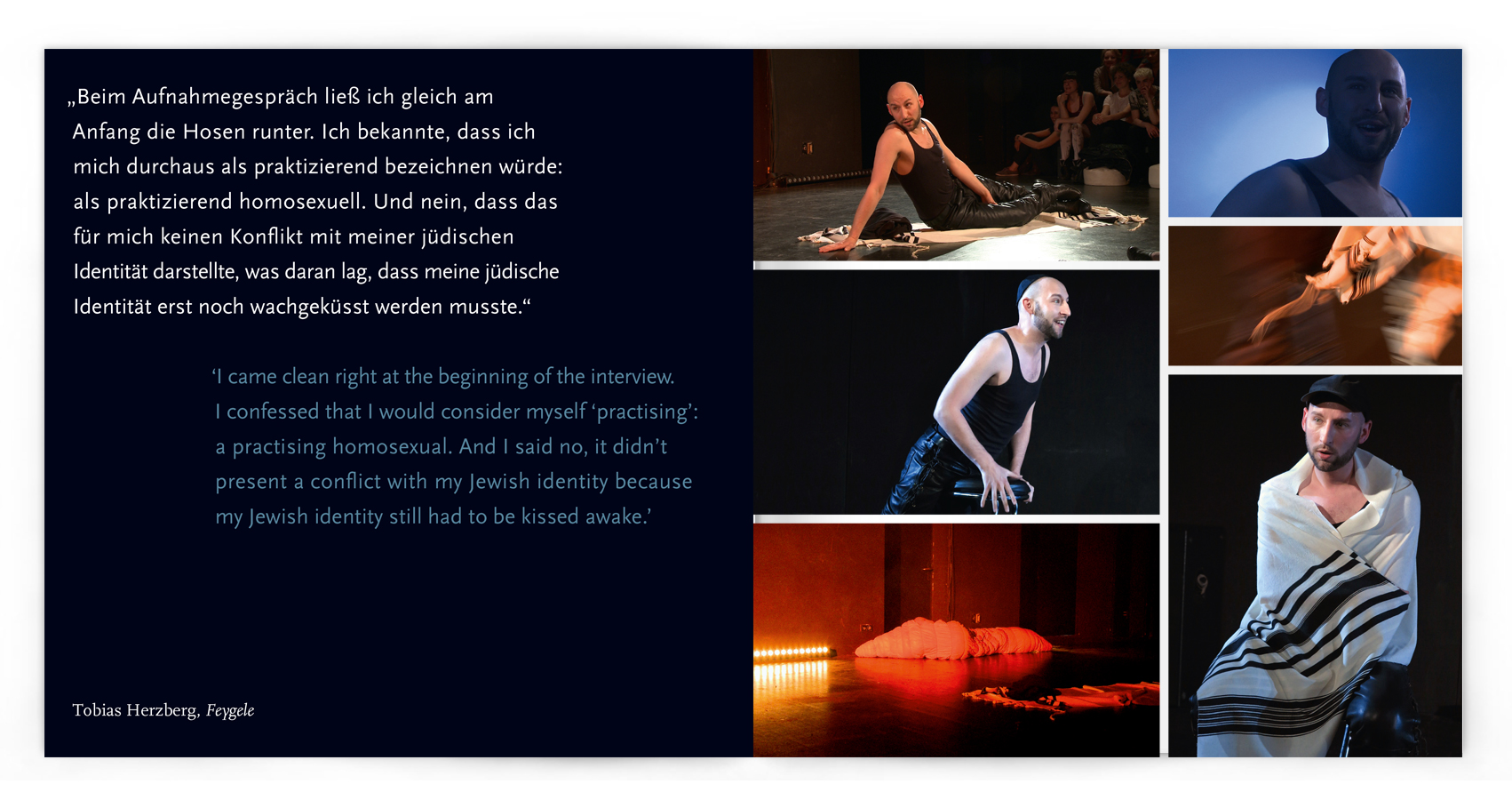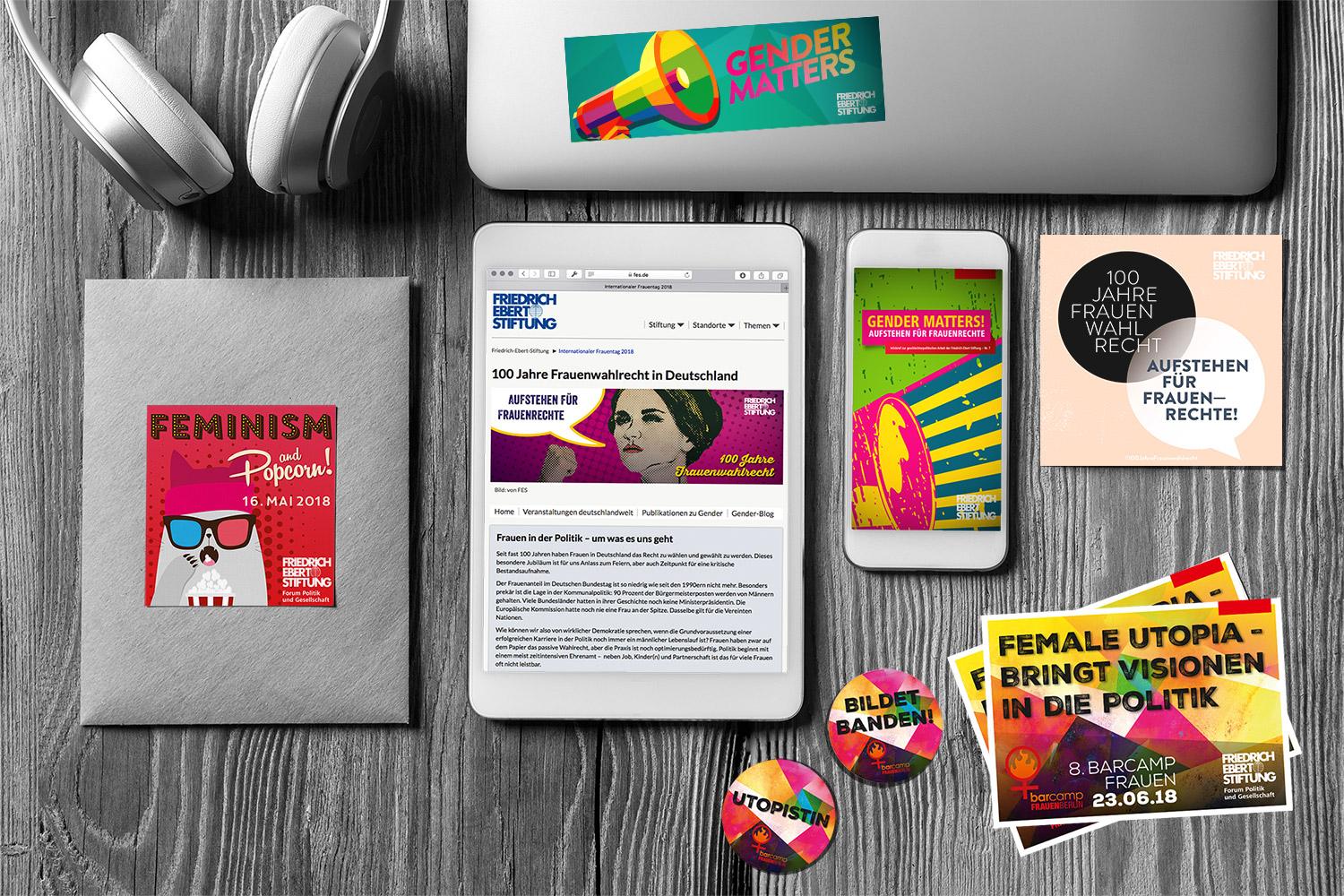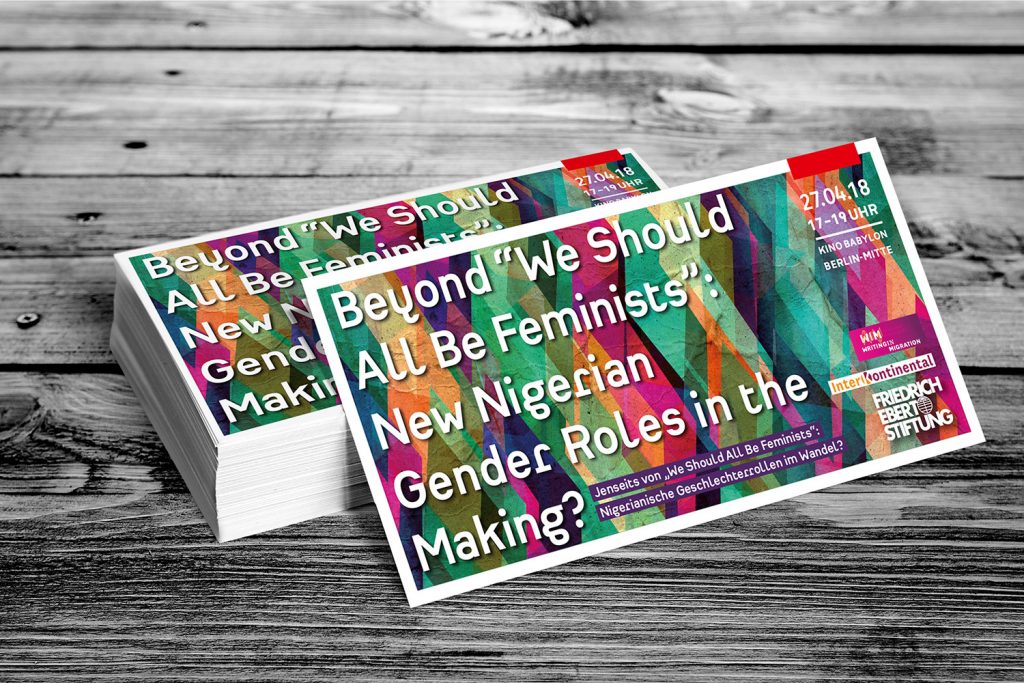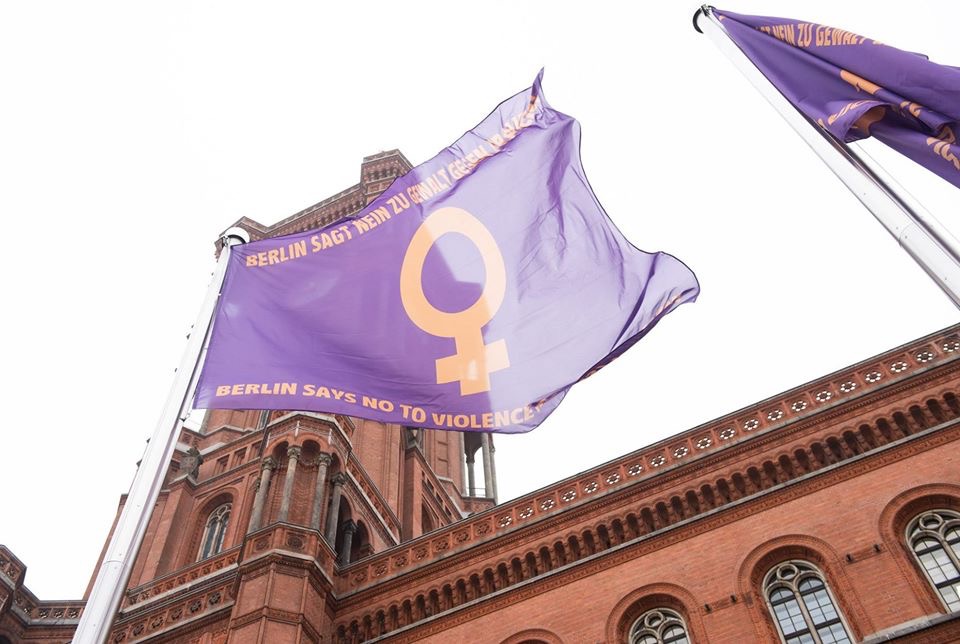
Visuelle Kommunikation // Editorial Design – Chapbooks // August 2020
Im Verlagshaus Berlin haben wir eine neue Reihe für Chapbooks entwickelt: In der edition zwanzig erscheinen Chapbooks, die Lust machen auf das Entdecken neuer poetischer Stimmen. Wir wollen Autor*innen eine erste Plattform zur Publikation und Zusammenarbeit bieten, noch bevor ein umfangreiches Manuskript in üblicher Debutlänge vorliegt.
Für die neue Edition habe ich das gestalterische Konzept entwickelt: handliche Bücher mit Klappumschlag, Fadenknotenbindung und gedruckt auf Fedrigoni´s neuem Arena-Papier leuchten im sommerlich frischen Pantone 811. Kleine typografische Schätze, die dazu einladen, neue Lyrik zu entdecken.
In unserer ersten Edition erschienen »BARBARA« von Barbara Juch und »lustdorf« von Alisha Gamisch starke lyrische Stimmen, die noch viel von sich hören lassen werden.
Visuelle Kommunikation // Gestaltung von Logo & Printmedien // August 2020
Das Projekt »Dagesh. Jüdische Kunst im Kontext« engagiert sich für Bildung und Vermittlung jüdischer Gegenwartskünste. Gestaltung von Logo, Falzflyer für das Bildungsprogramm »DAGESH on Tour« und Visitenkarten. → www.dagesh.de
Visuelle Kommunikation // Essay & Editorial Design // Dietz Verlag // August 2020
Von Franziska Richter, der Herausgeberin der Anthologie »Echoräume des Schocks« wurde ich neben vielen anderen Kreativen und Kulturschaffenden eingeladen, einen Text zur Anthologie über die Zeit des Lockdown beizusteuern. Entstanden ist der Essay »Ich glaube an die Chance, die in Vagheit liegt«, der persönliche Erfahrungen in meinen Rollen als Verlegerin, Typografin und Lehrende in einer Zeit großer Unsicherheiten reflektiert. Den Essay könnt ihr ab Seite 66 direkt im Buch nachlesen.
In 25 Beiträgen zeichnen Kulturschaffende und Kreative den Widerhall dieser Zeit auf, berichten von Ereignissen aus Politik und Gesellschaft und erzählen von Ängsten und Hoffnungen in ihrem Alltag im Ausnahmezustand. Sie vermessen den Schock, der den Kulturbereich getroffen hat und stellen sich die Frage, wie Kunst und Kultur in und nach der Corona-Zeit gefördert beziehungsweise gestärkt werden können.
ECHORÄUME DES SCHOCKS
Wie uns die Corona-Zeit verändert
Reflexionen Kulturschaffender und Kreativer
Franziska Richter (Hg.)
Gestaltet wurde das Buch von Typografie/im/Kontext.
Visuelle Kommunikation // Typedesign // August 2020
Luca Pacioli (1445-1514 oder 1517) war ein italienischer Mathematiker, der Lehrer von Leonardo da Vinci, Schachspieler, Zauberer und Typedesigner. Er hat für sein Buch »Divina Proportione« eine nahezu perfekte Schrift konstruiert – nahezu perfekt, denn vier Buchstaben fehlen: J, U, W und Z. Für das unglaubliche, über 800 Seiten schwere Buch »Die Welt der Renaissance«, hg. von Tobias Roth im Verlag Kiepenheuer & Witsch habe ich diese vier Buchstaben nachinterpretiert. Es war eine große Freude, mich dem Konstruktionsprinzip von Pacioli anzunähern! Nachschauen könnt ihr es in dem Buch, welches im Herbst 2020 erscheint!
Verlagshaus Berlin // Editorial Design // März 2020
→ made in china
Gedichte: Lea Schneider // Illustrationen: Yi Meng Wu
Buchgestaltung: Andrea Schmidt
Visuelle Kommunikation // Corporate Design // Senatsverwaltung Berlin // März 2020
Am Freitag, 6. März 2020, wurde im Rathaus der Berliner Frauenpreis an Yvonne Büdenhölzer, Intendantin der Berliner Festspiele, verliehen. Sie führte 2019 die Quote ein und ermöglichte damit eine größere Sichtbarkeit von Regisseurinnen im Rahmen des Berliner Theatertreffens! »Ein Sinneswandel ist im Theater von Nöten, ein generelles Umdenken, wenn Theater relevant bleiben will, erklärt sie, und um Strukturen zu schaffen brauche es Entscheidungen.« Es Ist großartig und wichtig, dass es diesen Preis gibt. Er schafft Sichtbarkeit für kluge, engagierte Frauen! Und ich bin sehr glücklich, dass ich mit Typografie/im/Kontext die visuelle Gestaltung für den Preis, der von der Senatsverwaltung für Gesundheit, Pflege und Gleichstellung ausgeschrieben wurde, übernehmen durfte.
Verlagshaus Berlin // Editorial Design // März 2020
→ Teilchenland
Gedichte: Caca Savic // Illustrationen: Nina Kaun
Buchgestaltung: Andrea Schmidt
Visuelle Kommunikation // Text-Bild-Performance // Schauspielhaus Hamburg // Dezember 2019
Visuelle Kommunikation // Gestaltung einer Flagge / Senatsverwaltung Berlin // November 2019
Auf Initiative von Senatorin Dilek Kalayci zeigt das Land Berlin erstmalig eine eigene Flagge zum Internationalen Aktionstag gegen Gewalt an Frauen. Senatorin Kalayci und Staatssekretärin Sawsan Chebli hissten gemeinsam die Flagge vor dem Roten Rathaus. (Entwurf der Flagge im Auftrag der Senatsverwaltung für Gesundheit, Pflege und Gleichstellung: Typografie/im/Kontext)